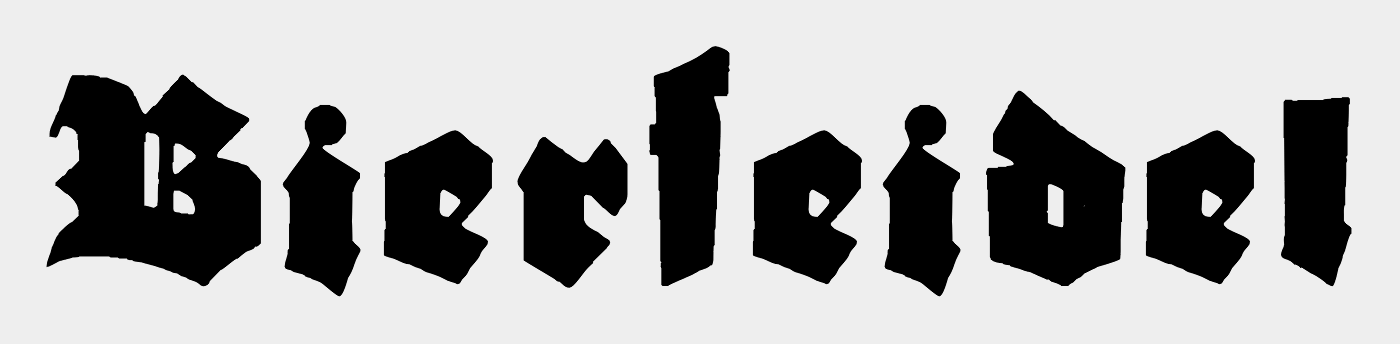
Suche Schrift von uriger Gastronomie
ich suche schon seit geraumer Zeit nach der passenden Font für folgendes Bild:
Die Schrift ähnelt "Old English Text MT", allerdings unterscheiden sich das großgeschriebene B doch deutlich.
Das B sieht echt sehr sehr ähnlich aus, dahingegen passt das kleine "s" nicht mehr.
Eventuell muss ich dann aber mit einer Mischung auskommen.
Doch, doch, das kleine s passt schon. In deinem Bild ist es nur falsch verwendet, weil beim Anlaut das von mir verwendete Lang-s verwendet werden soll. Ob der Font ein normales s an Bord hat, müsstest du nachschauen …
Für Leute, welche die klassische Schreibweise bei gebrochenen Schriften gewohnt sind, steht da nämlich nicht Bier-Seidel, sondern Biers-Eidel, wobei man sich fragt, was des Biers Eidel denn wohl ist :-)
Die "Ganz Grobe Gotisch" aus Dieter Steffmanns digitalisierung, jedoch um einige Ligaturen erweitert, und mit ſ (auf dem offiziellen Unicode-Platz U+017F) und dem "runden s" an dem üblichen Platz gibt es auch bei mir:
Für Leute, welche die klassische Schreibweise bei gebrochenen Schriften gewohnt sind, steht da nämlich nicht Bier-Seidel, sondern Biers-Eidel, …
Auch die werden beim Betrachten des Schildes mitbekommen, dass man dort Durst oder Durſt löschen kann, je nach Gusto oder Guſto :-). Die größere Gemeinde der Durstigen wird sich eher vom Bierseidel denn vom Bierſeidel angesprochen fühlen, und da auch Schrift dem Wandel unterliegt, wäre das s an dieser Stelle hinnehmbar.